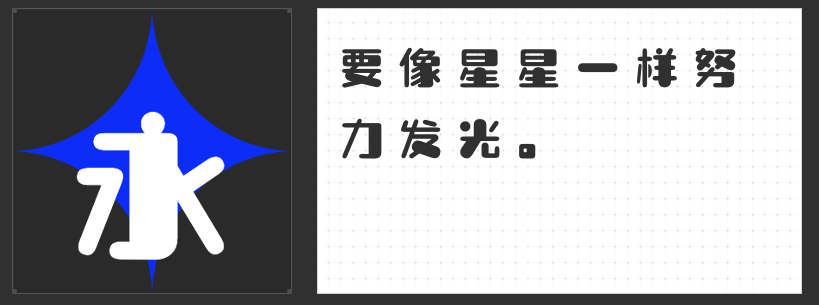
广告设计中的字体美学:四款风格化字库解锁创意表达
在广告设计的视觉语言体系中,字体不仅是信息载体,更是情感传递与品牌调性的核心媒介。以下四款各具特色的字库字体,以独特的设计哲学与美学表达,为广告创意提供多元解决方案。
一、励字志向黑简
励字志向黑简以黑体为基底,融入圆体设计语言,通过笔画拐角的外圆角处理,在硬朗的几何结构中注入柔和韵律。这种刚柔并济的视觉张力,既保留了黑体的理性秩序感,又通过微弧转角打破传统黑体的机械感,形成屏显场景下的视觉舒适区。其字面充实、结构稳定的特点,尤其适合科技、金融等需要传递专业信任感的行业广告,在保持视觉冲击力的同时,通过细节处的灵动设计避免刻板印象。
二、励字敲可爱简
励字敲可爱简以手写圆润线条重构字体形态,通过省略非关键笔画与简化结构,创造出兼具辨识度与童趣的视觉符号。其明快的线条节奏与随性书写感,在保留文字可读性的前提下,构建出充满想象力的视觉空间。这款字体天然适配母婴、文创、休闲食品等领域的广告设计,通过手绘质感传递温暖情感,用稚拙笔意唤醒受众的童心记忆,形成差异化品牌认知。
三、高手字斋东京体
东京体突破传统长形字结构,以等宽方块字型重构视觉秩序,粗体敦厚的笔画与锋利转折形成强烈对比,在横竖排版中均能保持清晰可读性。其光洁平滑的曲线处理既保留书写韵味,又通过现代设计语言提升视觉精致度。符号系统与字形的高度统一,使这款字体在文化类、高端消费品广告中展现出独特优势——既能承载传统文化底蕴,又能以简洁有力的视觉语言触达现代受众。
四、喵字芒果体
专为芒果农产品设计的芒果体,将果实形态转化为字体基因:圆润流畅的笔画模拟芒果饱满轮廓,线条粗细变化呼应多汁质感,整体视觉传递出热带阳光的温暖气息。这款字体通过形态仿生设计,在文字层面即完成产品特性的视觉转译,天然适配农产品包装、食品广告等场景,用字体设计强化“新鲜”“自然”的核心诉求,形成从视觉到味觉的通感体验。
设计师可根据品牌调性、产品特性与传播场景,选择最具契合度的字体语言,让文字成为传递价值的第一触点。